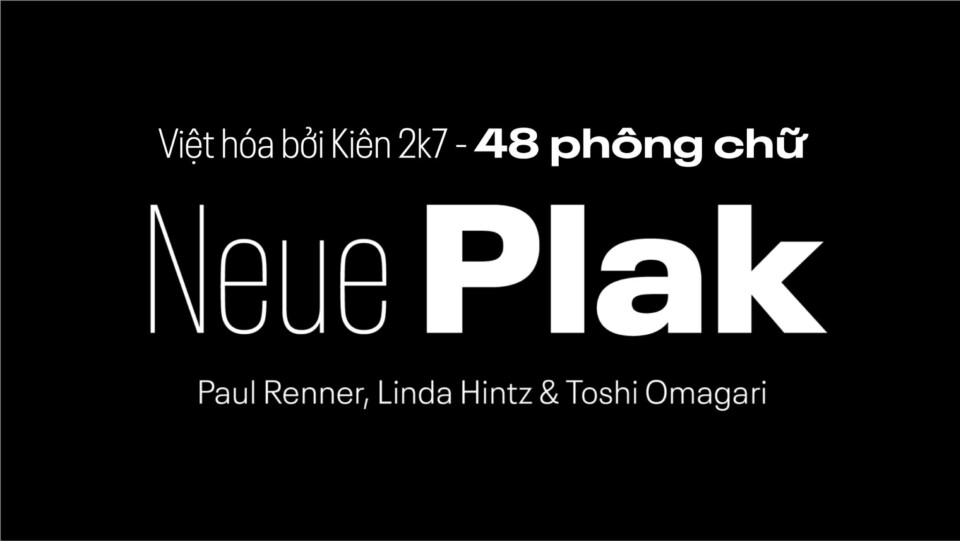
Giới thiệu về bộ Font Việt Hóa Neue Plak
Trong thế giới đồ họa hiện đại, việc lựa chọn Font Chữ phù hợp đóng vai trò quyết định đến thẩm mỹ của sản phẩm. Font Việt Hóa Neue Plak là một sự kế thừa hoàn hảo từ phong cách Futura cổ điển nhưng được cải tiến với vẻ ngoài mạnh mẽ và linh hoạt hơn. Bộ font này không chỉ mang lại cảm giác chuyên nghiệp mà còn giúp các bạn học sinh, sinh viên dễ dàng trình bày bài tập lớn hay các dự án truyền thông tại nhà trường một cách ấn tượng nhất.
Đặc điểm nổi bật của Font Việt Hóa Neue Plak
Thiết kế hiện đại và tối giản
Được lấy cảm hứng từ những thiết kế biểu bảng tại Đức, bộ Font Việt Hóa Neue Plak sở hữu các đường nét dứt khoát cùng độ tương phản thấp. Điều này giúp văn bản trở nên cực kỳ dễ đọc ngay cả ở kích thước nhỏ hoặc trên các màn hình có độ phân giải thấp. Với bảng mã được tinh chỉnh kỹ lưỡng, người dùng tại Việt Nam có thể hoàn toàn yên tâm khi sử dụng các ký tự tiếng Việt có dấu mà không lo bị lỗi hiển thị hay mất nét.
Tính ứng dụng đa dạng trong học đường
Nhờ sự đa dạng về độ dày (weight), từ mỏng nhẹ đến đậm nét, font chữ này phù hợp cho nhiều mục đích khác nhau. Bạn có thể dùng Font Việt Hóa Neue Plak để thiết kế tiêu đề slide bài giảng, làm báo cáo khoa học hay tạo poster cho các sự kiện CLB. Sự cân bằng giữa tính nghệ thuật và tính ứng dụng giúp bộ font này trở thành lựa chọn hàng đầu cho những ai yêu thích sự tinh tế và gọn gàng.